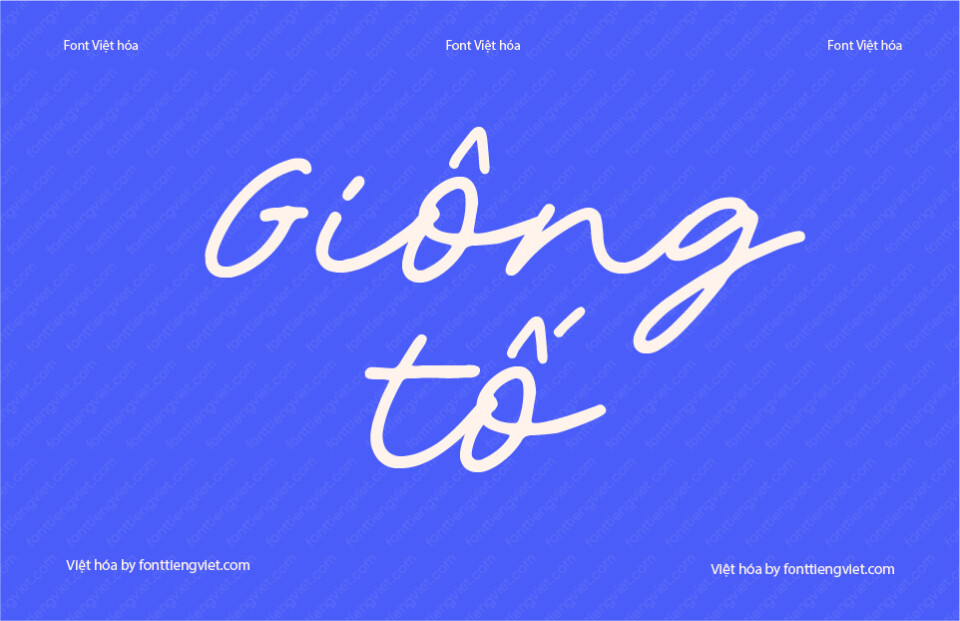
Trong thế giới của thiết kế đồ họa và sáng tạo nội dung số, việc lựa chọn một Font Chữ đẹp và phù hợp có vai trò cực kỳ quan trọng. Nó không chỉ thể hiện phong cách cá nhân mà còn góp phần truyền tải thông điệp một cách hiệu quả nhất. Đặc biệt, với sự phát triển của tiếng Việt, các font chữ được Việt hóa ngày càng trở nên cần thiết. Hôm nay, chúng ta sẽ cùng đi sâu khám phá một biểu tượng mới trong cộng đồng thiết kế: Font Việt hóa 1FTV VIP Dear Crush. Đây không chỉ là một font chữ thông thường mà còn là nguồn cảm hứng bất tận cho những ai đang tìm kiếm sự tinh tế và độc đáo trong từng đường nét.
Font Việt hóa 1FTV VIP Dear Crush: Đặc Điểm Nổi Bật và Ứng Dụng Sáng Tạo
Font Việt hóa 1FTV VIP Dear Crush nổi bật với phong cách viết tay mềm mại, tự nhiên nhưng vẫn giữ được sự rõ ràng và dễ đọc. Điểm mạnh lớn nhất của font này chính là khả năng Việt hóa hoàn chỉnh, bao gồm đầy đủ các dấu thanh, ký tự đặc biệt của tiếng Việt, giúp người dùng dễ dàng tạo ra những văn bản tiếng Việt đẹp mắt mà không lo lỗi font hay thiếu ký tự. Mỗi đường nét đều được chăm chút tỉ mỉ, tạo nên một tổng thể hài hòa, mang đến cảm giác thân thiện và gần gũi. Đây là một sự lựa chọn tuyệt vời cho các dự án cần sự lãng mạn, cá nhân hóa cao.
Thiết Kế Độc Đáo và Thẩm Mỹ Cao
Sự độc đáo của Font Việt hóa 1FTV VIP Dear Crush đến từ sự kết hợp giữa nét hiện đại và chút hoài cổ, tạo nên một phong cách typography rất riêng. Các chữ cái có độ cong mềm mại, thanh thoát, dễ dàng thu hút ánh nhìn và tạo điểm nhấn cho bất kỳ thiết kế nào. Với độ dày nét vừa phải, font này đảm bảo tính thẩm mỹ dù được sử dụng ở kích thước lớn hay nhỏ, trên các nền màu sắc khác nhau. Đây là yếu tố then chốt giúp các tác phẩm của bạn trở nên chuyên nghiệp và ấn tượng hơn.
Ứng Dụng Đa Dạng Trong Mọi Lĩnh Vực
Khả năng ứng dụng của Font Việt hóa 1FTV VIP Dear Crush là vô cùng phong phú. Với vẻ đẹp tinh tế của mình, font này rất phù hợp cho các dự án như:
- Thiết kế thiệp mời: Từ thiệp cưới, sinh nhật đến các sự kiện đặc biệt, font Dear Crush sẽ mang lại cảm giác ấm áp và cá nhân hóa.
- Brand identity (nhận diện thương hiệu): Tạo logo, slogan cho các thương hiệu thời trang, quán cà phê, tiệm bánh ngọt hay các dịch vụ handmade.
- Ấn phẩm truyền thông: Poster, banner quảng cáo, brochure, tạp chí cần một phong cách mềm mại, nữ tính.
- Thiết kế website và blog: Sử dụng cho tiêu đề, trích dẫn hoặc các phần nội dung cần sự nhấn nhá, tạo cảm giác thân thiện với người đọc.
- Đóng gói sản phẩm: Mang đến vẻ ngoài độc đáo và thu hút cho bao bì sản phẩm.
- Mạng xã hội: Các bài đăng, story trên Instagram, Facebook sẽ trở nên sinh động và cuốn hút hơn.
Lợi Ích Khi Sử Dụng Font Việt hóa 1FTV VIP Dear Crush
Việc lựa chọn Font Việt hóa 1FTV VIP Dear Crush mang lại nhiều lợi ích đáng kể cho các nhà thiết kế và người sáng tạo nội dung:
- Tiết kiệm thời gian: Với khả năng Việt hóa hoàn chỉnh, bạn không cần phải tốn công điều chỉnh từng ký tự hay lo lắng về việc font bị lỗi khi hiển thị tiếng Việt.
- Nâng cao tính thẩm mỹ: Phong cách độc đáo của font giúp các thiết kế trở nên nổi bật và chuyên nghiệp hơn, thu hút sự chú ý từ người xem.
- Đa dạng hóa phong cách: Font Dear Crush mở ra nhiều khả năng sáng tạo, giúp bạn thể hiện cá tính riêng và tạo ra những tác phẩm không trùng lặp.
- Tăng cường trải nghiệm người dùng: Đối với website hoặc ứng dụng, một font chữ dễ đọc và đẹp mắt sẽ cải thiện đáng kể trải nghiệm của người dùng.
Với sự phát triển không ngừng của công nghệ và thị hiếu thẩm mỹ, việc cập nhật và sử dụng những font chữ chất lượng cao như Font Việt hóa 1FTV VIP Dear Crush là điều cần thiết để duy trì sự cạnh tranh và sáng tạo trong lĩnh vực thiết kế. Đây không chỉ là một công cụ mà còn là một nguồn cảm hứng, giúp bạn biến những ý tưởng thành hiện thực một cách hoàn hảo nhất.
Có thể nói, Font Việt hóa 1FTV VIP Dear Crush đã và đang khẳng định vị thế của mình trong lòng những người yêu thiết kế. Với vẻ đẹp tinh tế, khả năng ứng dụng linh hoạt và sự chăm chút trong từng ký tự Việt, font chữ này chắc chắn sẽ là một công cụ đắc lực giúp bạn tạo nên những tác phẩm ấn tượng và độc đáo. Đừng ngần ngại khám phá và tải về Font Chữ đặc biệt này để làm phong phú thêm bộ sưu tập font của bạn và đưa các dự án sáng tạo lên một tầm cao mới. Hãy để Font Việt hóa 1FTV VIP Dear Crush kể câu chuyện của bạn!